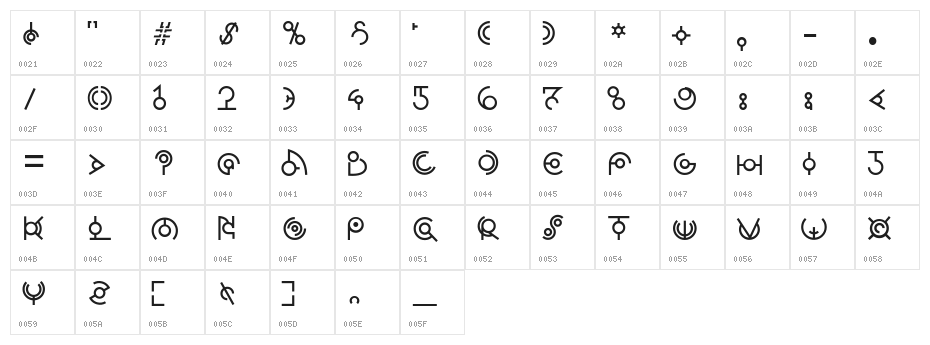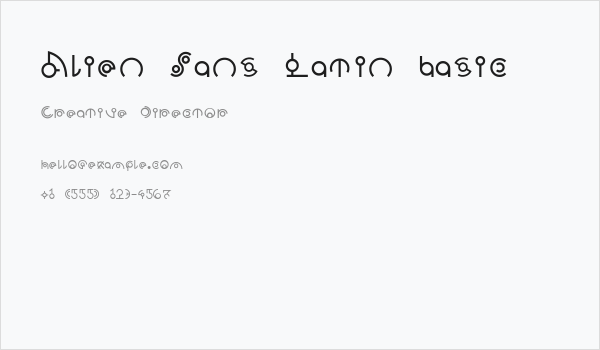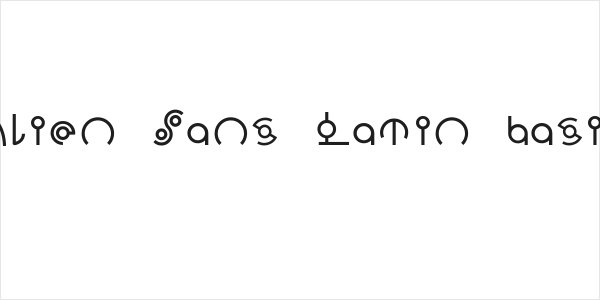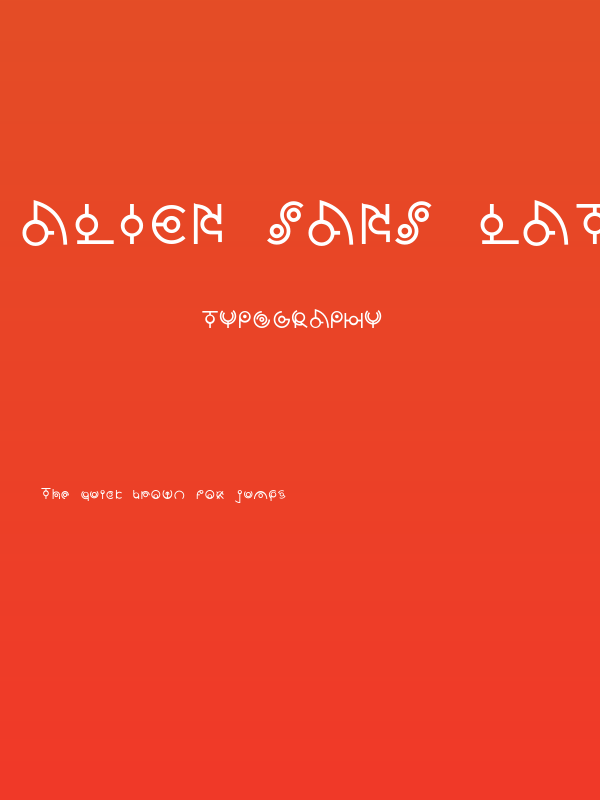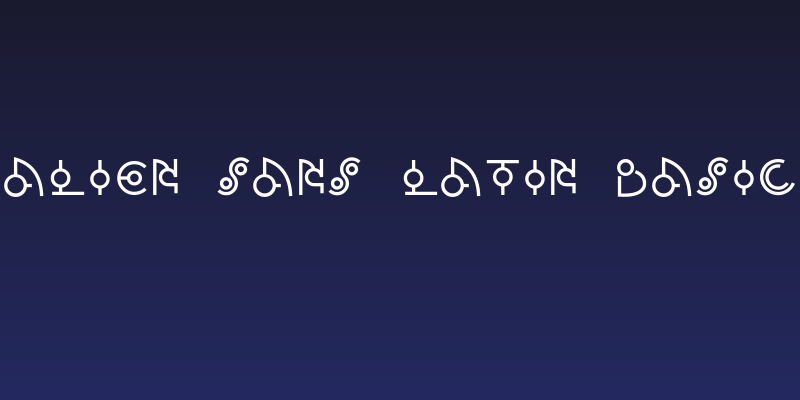
Alien Sans Latin basic Font
| Gesamtstil | Futuristic |
| Vorgeschlagene Projekte | Ideal for sci-fi themed projects, video game graphics, movie posters, and branding for tech startups. |